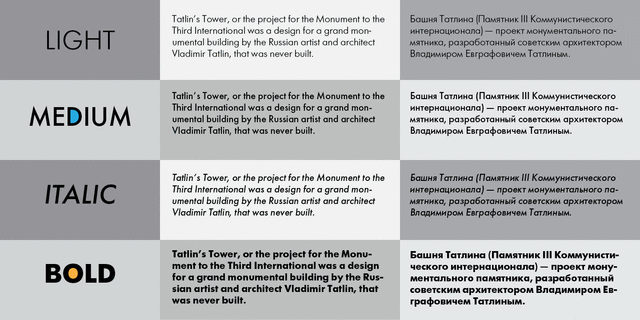
Гарнитура разработана в фирме ПараТайп (ПараГраф) в 1991–95 (дизайнер Владимир Ефимов) на основе рисунков гарнитуры Futura фирмы Bauersche Giesserei, 1927 (дизайнер Пауль Реннер). Футура является зарегистрированной Торговой маркой фирмы Neufville, SL.
Ассоциации c начертанием Futura Futuris MediumКачества и характер:
лаконичный, городской, точный, строгий, чертежный, инженерный, глобализированный, глобалистичный, архитектурный, умный, чистый, простой, современный
новости, инновации, архитектура, город, наука, интернет, мобильная связь, дизайн, одежда, обувь, айтишник, айти, IT, технологии, чертеж, инженер, архитектор, техника, химия, физика Стилистика:
Особенности семейства Futura FuturisХит десятилетия:
Хит 1930-х Хит 1980-х Хит 2010-х Этот шрифт в логотипах:
House MD, Ikea, Hewlett-Packard, Charite
Близкий исторический оригинал: